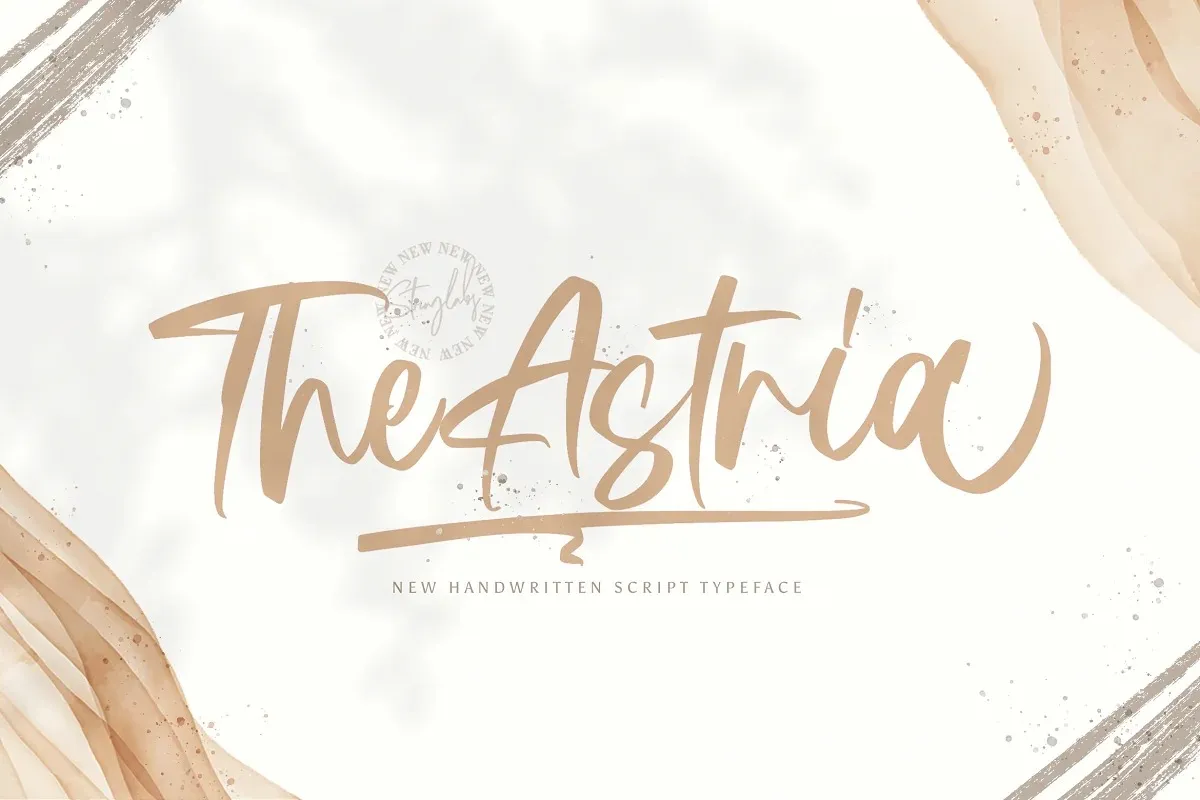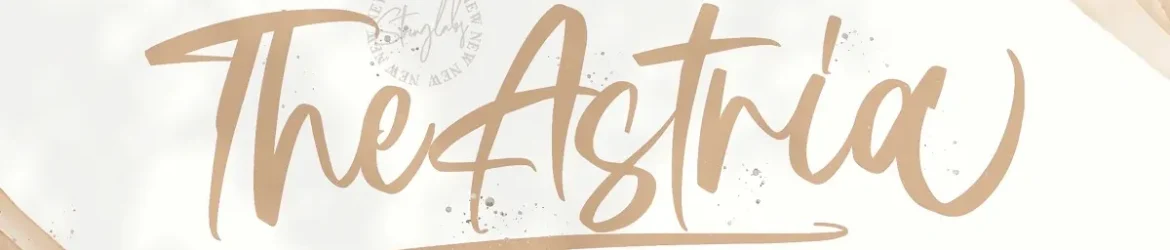
A Astria Font é uma elegante fonte de script desenvolvida pela StringLabs, conhecida por seu único texto e aparência cuidadosamente equilibrada. Esta fonte cria um estilo sofisticado que promete revolucionar suas ideias criativas, fazendo-as realmente vivas. Com caracteres belos e bem balanceados, a Astria é uma escolha perfeita para combinar com um vasto número de projetos. Seja em banners, gráficos ou letras menores, a Astria traz vida aos seus designs mais audaciosos, tornando-os ainda mais chamativos. Sua versatilidade significa que ela se adapta perfeitamente a uma variedade impressionante de estilos e tamanhos, garantindo um impacto visual atraente em qualquer projeto.